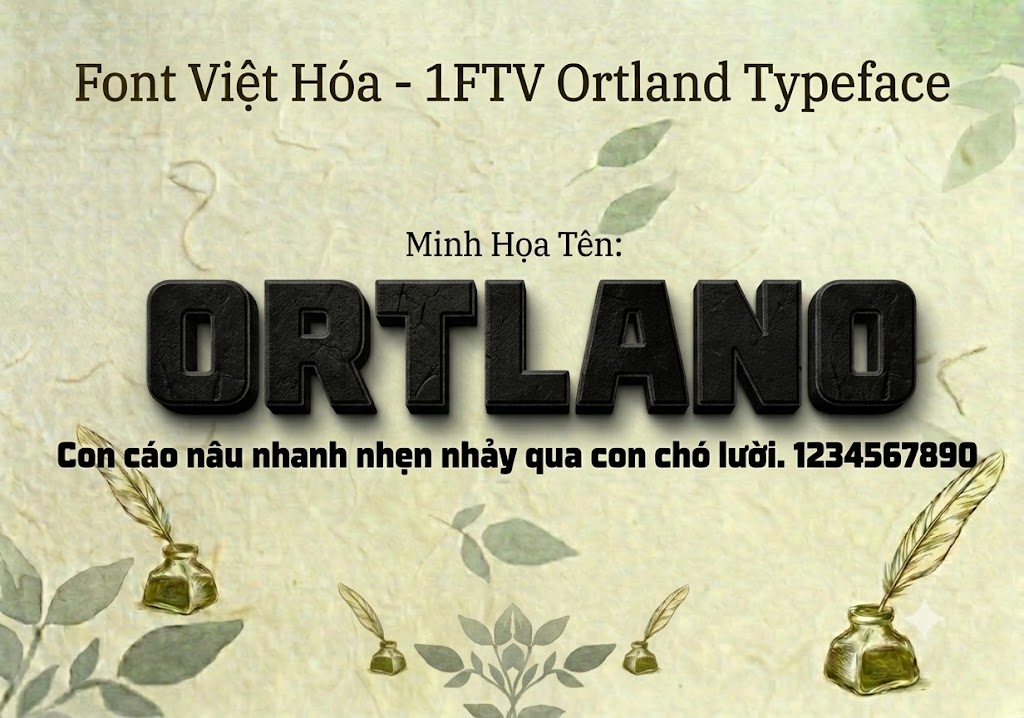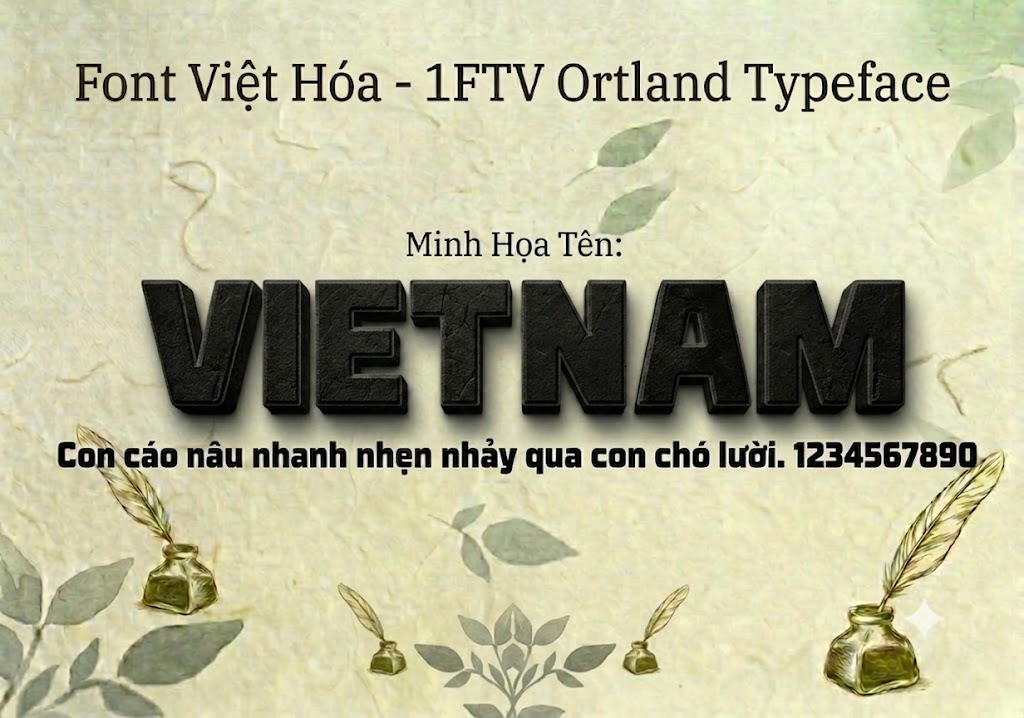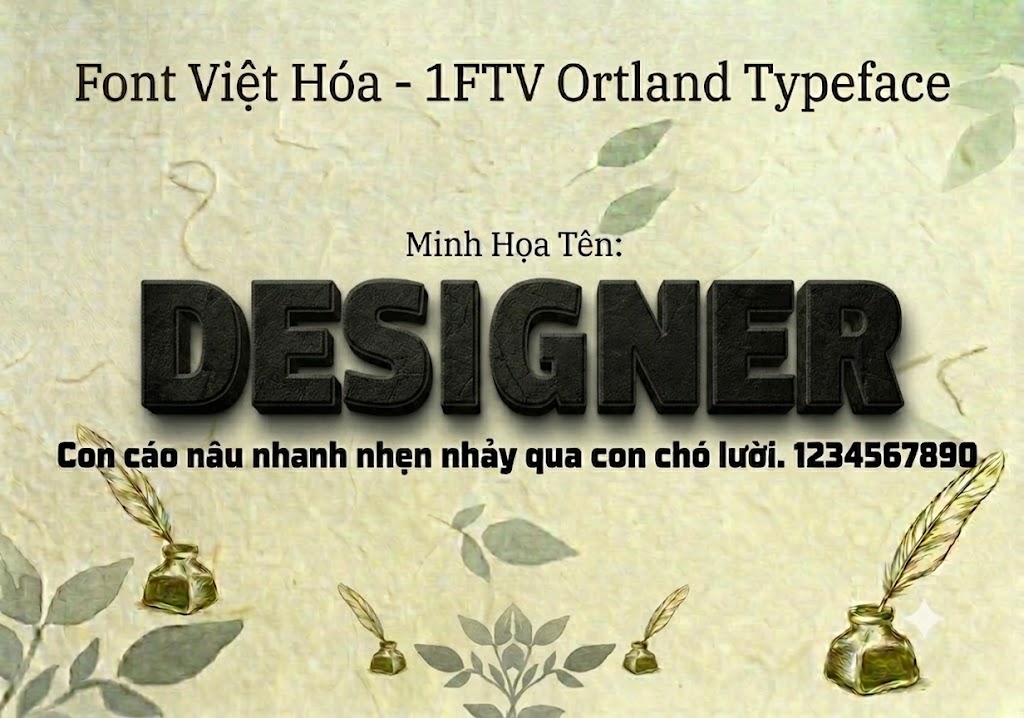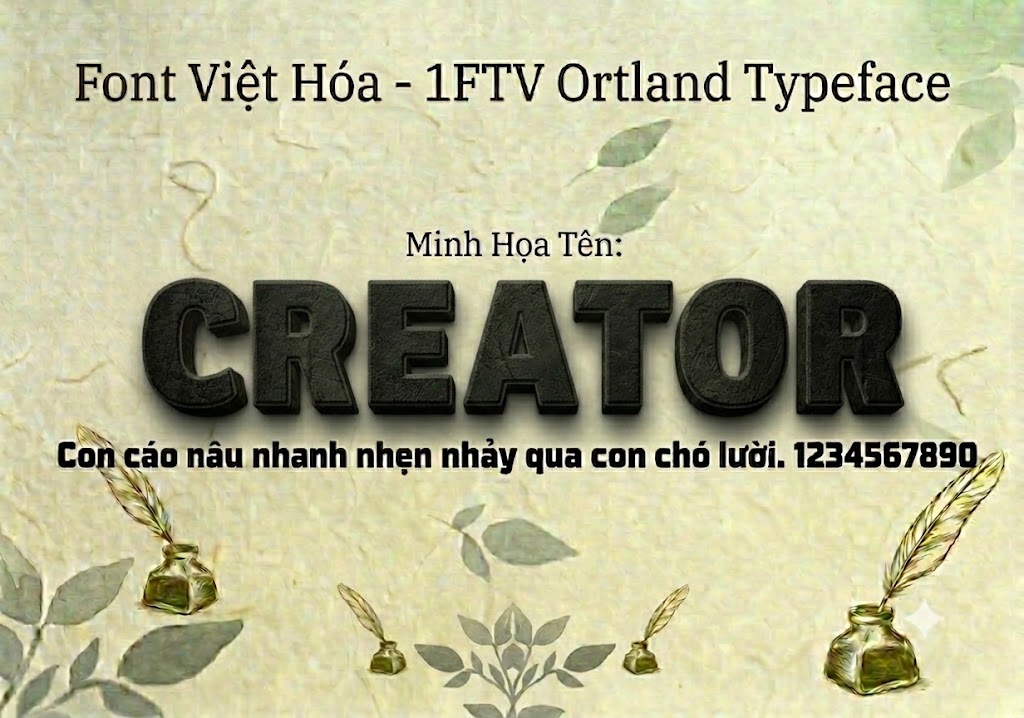
1FTV Ortland
Font 1FTV Ortland là một phông chữ display không chân nổi bật với cấu trúc hình khối vuông vắn, đầy đặn và mang phong cách hiện đại.
Bộ font này được tối ưu hóa kỹ lưỡng ở phiên bản 1.000, đem đến sự nhất quán và đồng bộ tuyệt đối trong cấu trúc của từng ký tự.
Đặc điểm nổi bật của phong cách thiết kế Ortland
Sức hút lớn nhất của font 1FTV Ortland đến từ phom chữ bo góc vuông vắn và đường nét siêu dày.
Các ký tự được tạo hình theo xu hướng khối hộp, tạo cảm giác kiên cố, vững chắc và vô cùng mạnh mẽ cho toàn bộ văn bản.
Khác với nhiều phông chữ dạng khối thường bị lược bỏ chữ thường, bộ font này hỗ trợ trọn vẹn cả hệ thống chữ lowercase và uppercase.
Nhờ đó bạn có thể linh hoạt phối hợp chữ hoa chữ thường để tiêu đề trở nên tự nhiên, dễ đọc và thoáng mắt hơn khi hiển thị.
Khoảng trống bên trong của các con chữ được tính toán khoa học, giúp văn bản luôn rõ ràng và không bị dính đặc khi bạn thu nhỏ bố cục thiết kế.
Để phông chữ vận hành mượt mà trên mọi hệ thống máy tính, phiên bản font 1FTV Ortland đã trải qua quy trình xử lý thông số kĩ thuật kỹ lưỡng.
Hệ thống khoảng cách chữ và độ giãn dòng đã được căn chỉnh chuẩn xác, giúp các từ khi đứng cạnh nhau luôn giữ được khoảng trống thẩm mỹ.
Bên cạnh hệ thống chữ cái hoa và thường đồng bộ, phông chữ còn tích hợp đầy đủ dãy số từ 0-9 cùng hệ thống các ký tự đặc biệt, dấu câu thông dụng (1234567890.:,;'"(!?)+-*/=).
Hình ảnh demo thực tế của font 1FTV Ortland
Để giúp bạn dễ dàng hình dung khả năng co giãn và hiển thị linh hoạt của phông chữ này trên các kích thước khác nhau, hãy cùng xem qua bảng mô phỏng thực tế:
Kích thước nhỏ (12pt – 24pt): Các nét chữ đậm và bộ chữ thường vẫn hiển thị rất rõ ràng, ngay ngắn, dễ đọc trên màn hình điện thoại di động.
Kích thước lớn (36pt – 72pt): Đây là không gian lý tưởng để font chữ phô diễn toàn bộ sức mạnh hình khối, tạo hiệu ứng thị giác đè nặng mạnh mẽ cho các tiêu đề chính.